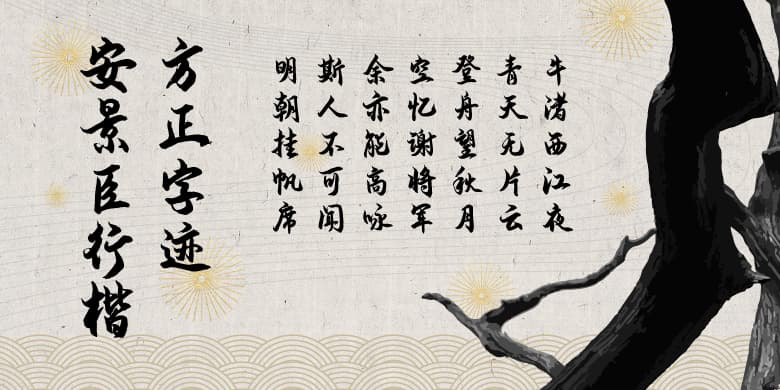
品牌:方正字迹设计师:安景臣发行时间:2021字库编码:大陆简体(GB2312-80)分类:常规书写·毛笔字体属性:精品字
安景臣行楷既有传统书法功底,又有鲜明的时代特色与个性风格。此款字体在吸收传统书法风格,诸如王羲之、米芾、赵孟頫等书法字体风格的基础上,加上借鉴现代任政行书等的特点,比传统书法更具规范性,同时比现有电脑行楷体灵活生动、更具文化气息与实用性,适用于传媒公司、大型企业、商家店铺广告标题等及排版印刷正文采用。